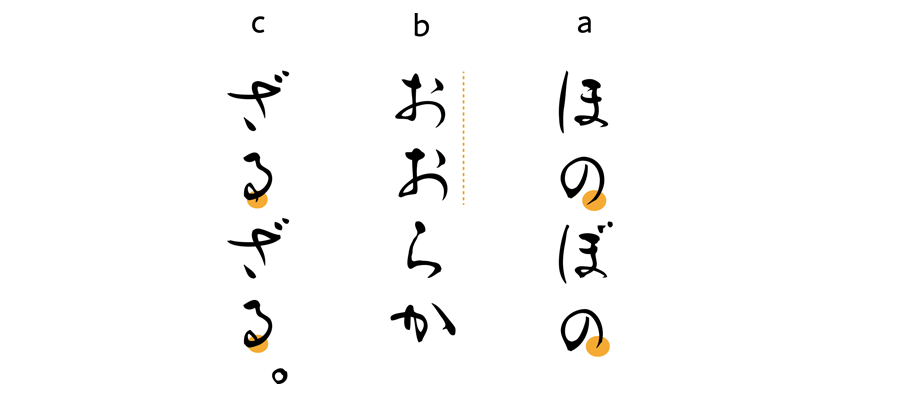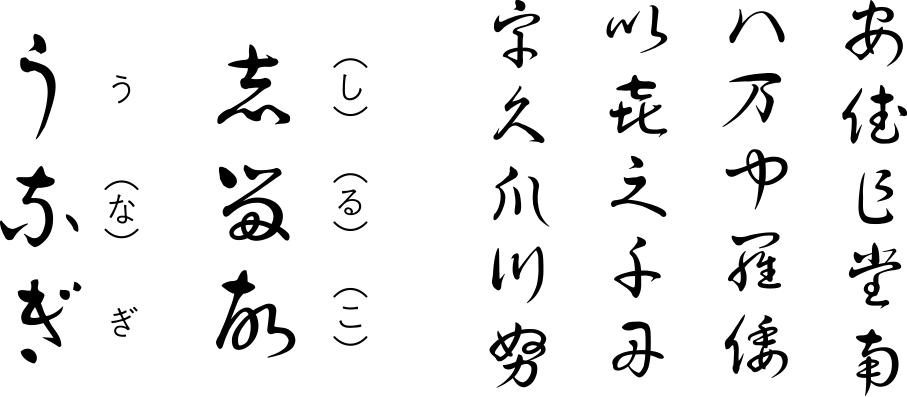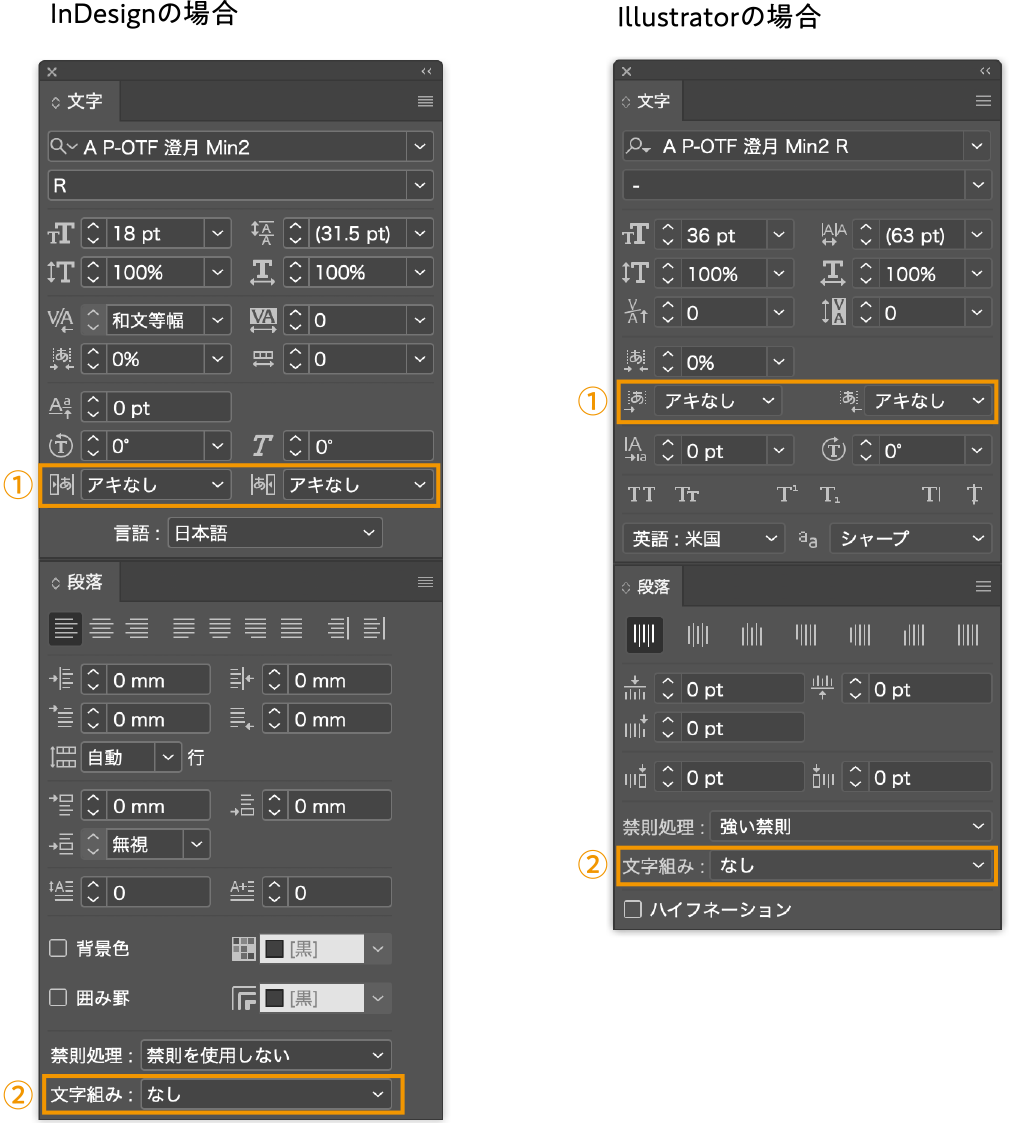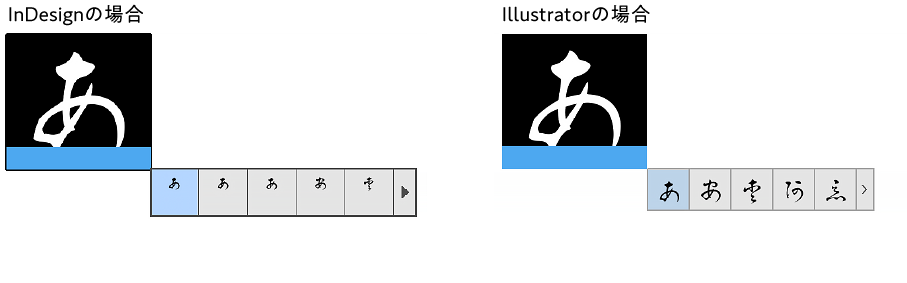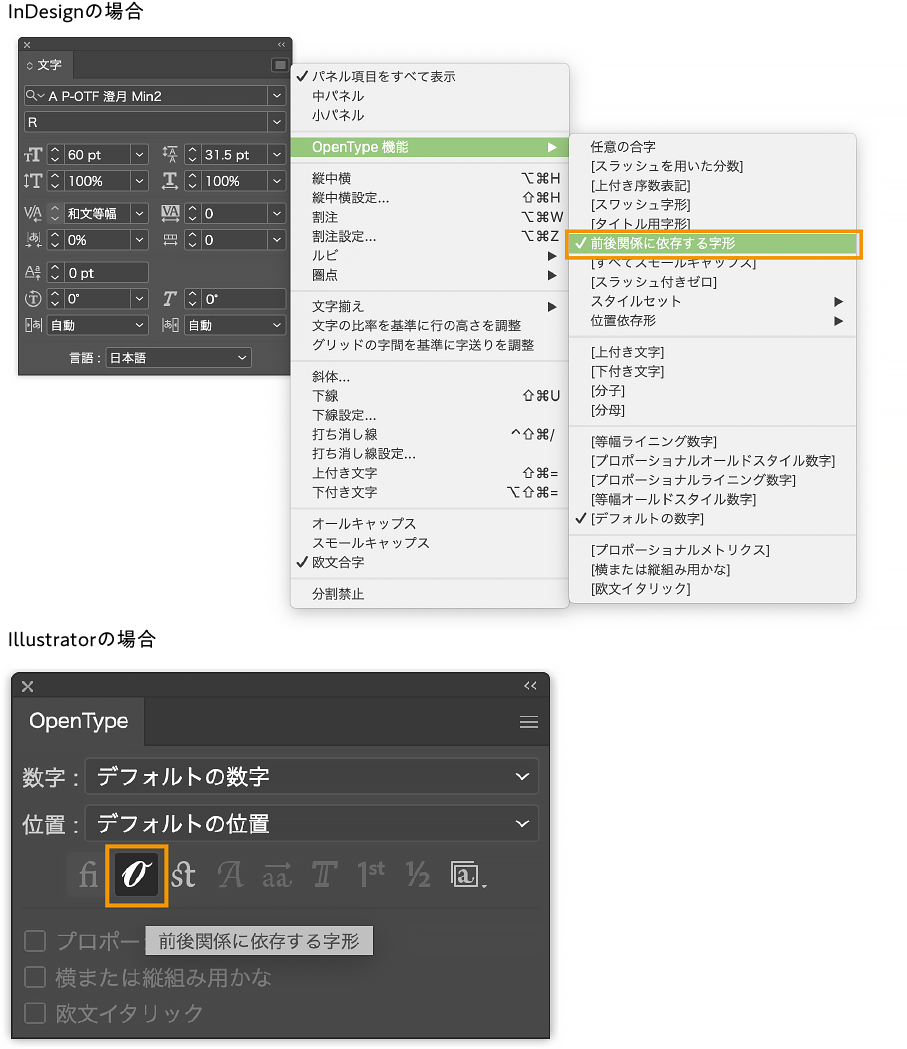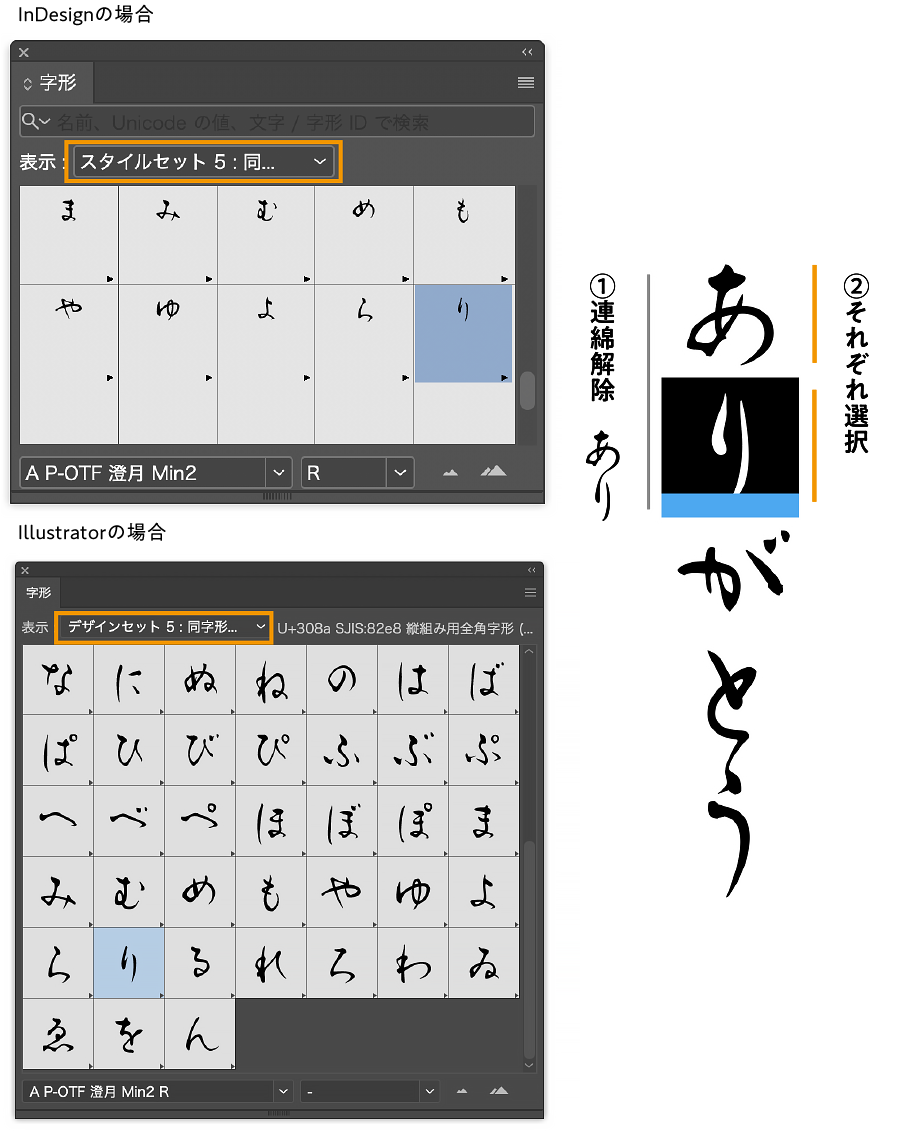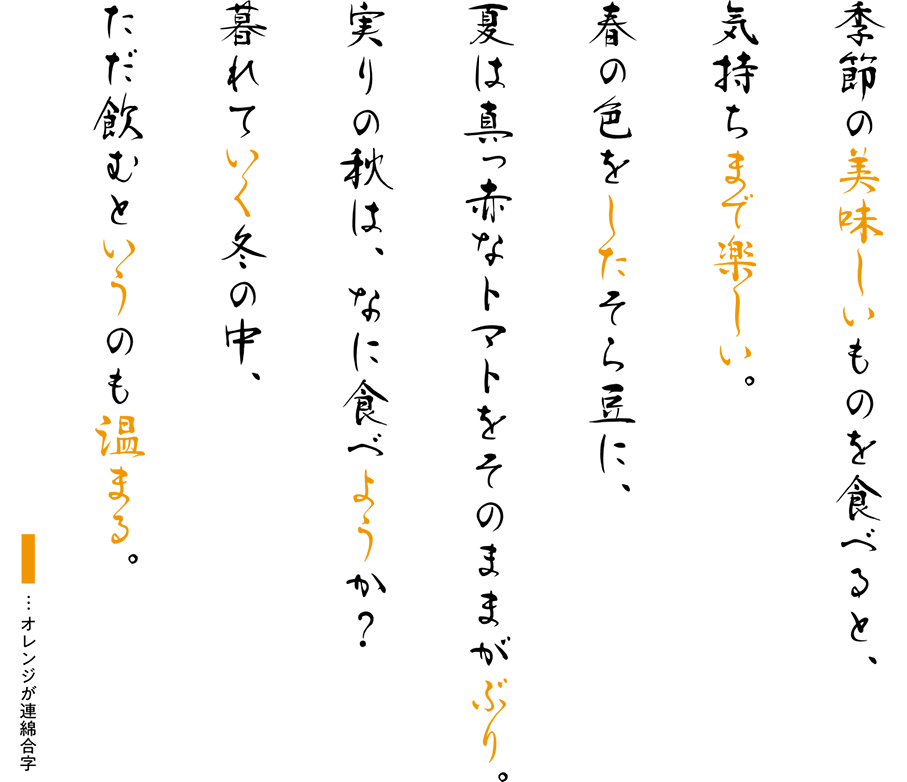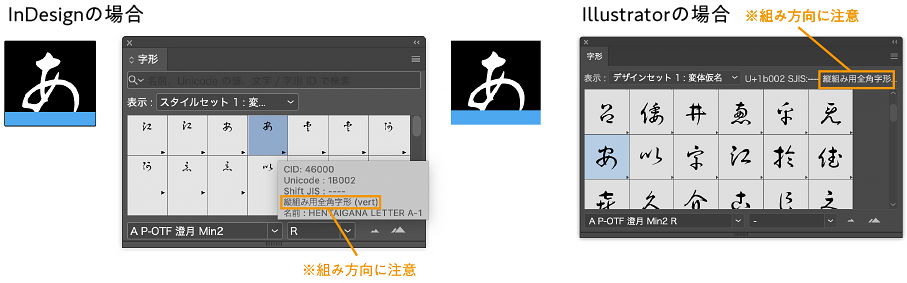
【澄月について】
澄月の特徴
澄月は当社独自の文字セットであるミニ2セットをサポートしますが、それ以外にも約800の連綿体や代替字形を用意しており、アプリケーション上の機能によって、連綿体(合字)などの文脈を考慮したデザインに自動で置き換わります。
文脈を考慮した字形
(1)連綿体(合字)
澄月は、特定の品詞において、手書きの続け字から着想を得た縦書き用の連綿体を用意しています。この連綿体は合字機能(複数の文字を合成して1文字に置換する機能)を活用し、自動で置き換わります。
(2)前後関係に依存して変化するかな
澄月では、1つのかなに対して、文脈によって自動で置き換わる複数のデザインを用意しています。
a.運筆考慮:直後に入力される文字との繋がり(文脈)を考慮した字形
b.連続回避:同じかなが連続して入力された場合に発動する字形
c.文末専用字形:改行や句点の前で発動する字形
(3)横組専用のかな
澄月は、手書き文字のかたちを考慮し、一部のかなに横組用のデザインを搭載しています。アプリケーション上のテキスト選択で横組を選択すると、自動で置き換わります。
フルプロポーショナルフォント
澄月は、全ての文字に固有の幅を持たせた、フルプロポーショナルフォントになっています。
変体仮名
澄月は、Unicodeに登録されている変体仮名286文字を収録しています。
澄月はプロポーショナルフォントであり、すべての文字に最適な幅が与えられているため、アプリケーション側での約物のアキの調整を必要としない書体になっています。
澄月は、ペアカーニングを搭載しています。
澄月は自動で変体仮名に置き換わる設定ではありません。
澄月では、連綿体等の文字のバリエーションが「自動」で置き換わるようになっています。(変体仮名を除く)
※澄月のスタイルセット詳細
・セット1:変体仮名
・セット2:基本的な連綿体(合字)
・セット3:行末用の連綿体(合字)
・セット4:その他の連綿体(合字)
・セット5:同字形の連続入力用の異体字(単体)
・セット6:前後関係に依存して変化する異体字(単体)
・セット7:行末用の異体字(単体)
■「異体字」について
本来「異体字」は、標準的な文字に対して字体の異なる文字のことを指します。
一方、本書体においては、Opentype属性の各種機能により代替字形の挙動を管理しているため、 Adobe InDesignおよび Adobe Illustrator のマニュアルの表現に合わせ、 変体仮名や前後関係に依存する別デザインのかなについても「異体字」と表現しています。